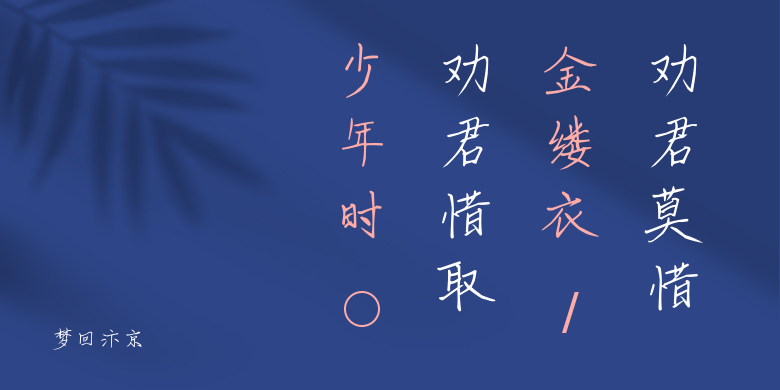
梦回汴京
梦回汴京,这款字体结构工整、笔画清晰,兼顾美观与易读性,适用于标题、正文、海报、包装、LOGO 等多种场景。字形优雅稳定,风格百搭耐看,适配日常排版与创意设计,让文字呈现更舒适、更具质感。梦回汴京一笔一画,皆是细节,以均衡的比例、流畅的线条打造舒适视觉体验,字形端正大气,风格简约现代。无论是商业设计、品牌宣传还是日常排版,都能轻松驾驭,让文字更有格调与力量。梦回汴京字体下载。